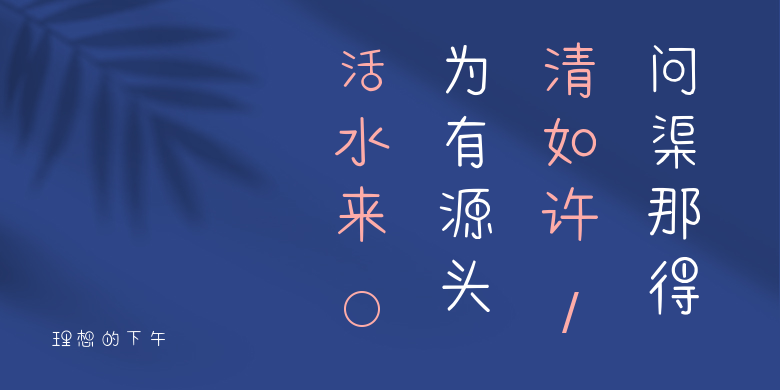
理想的下午
理想的下午,这款字体结构工整、笔画清晰,兼顾美观与易读性,适用于标题、正文、海报、包装、LOGO 等多种场景。字形优雅稳定,风格百搭耐看,适配日常排版与创意设计,让文字呈现更舒适、更具质感。理想的下午一笔一画,皆是细节,以均衡的比例、流畅的线条打造舒适视觉体验,字形端正大气,风格简约现代。无论是商业设计、品牌宣传还是日常排版,都能轻松驾驭,让文字更有格调与力量。理想的下午字体下载。